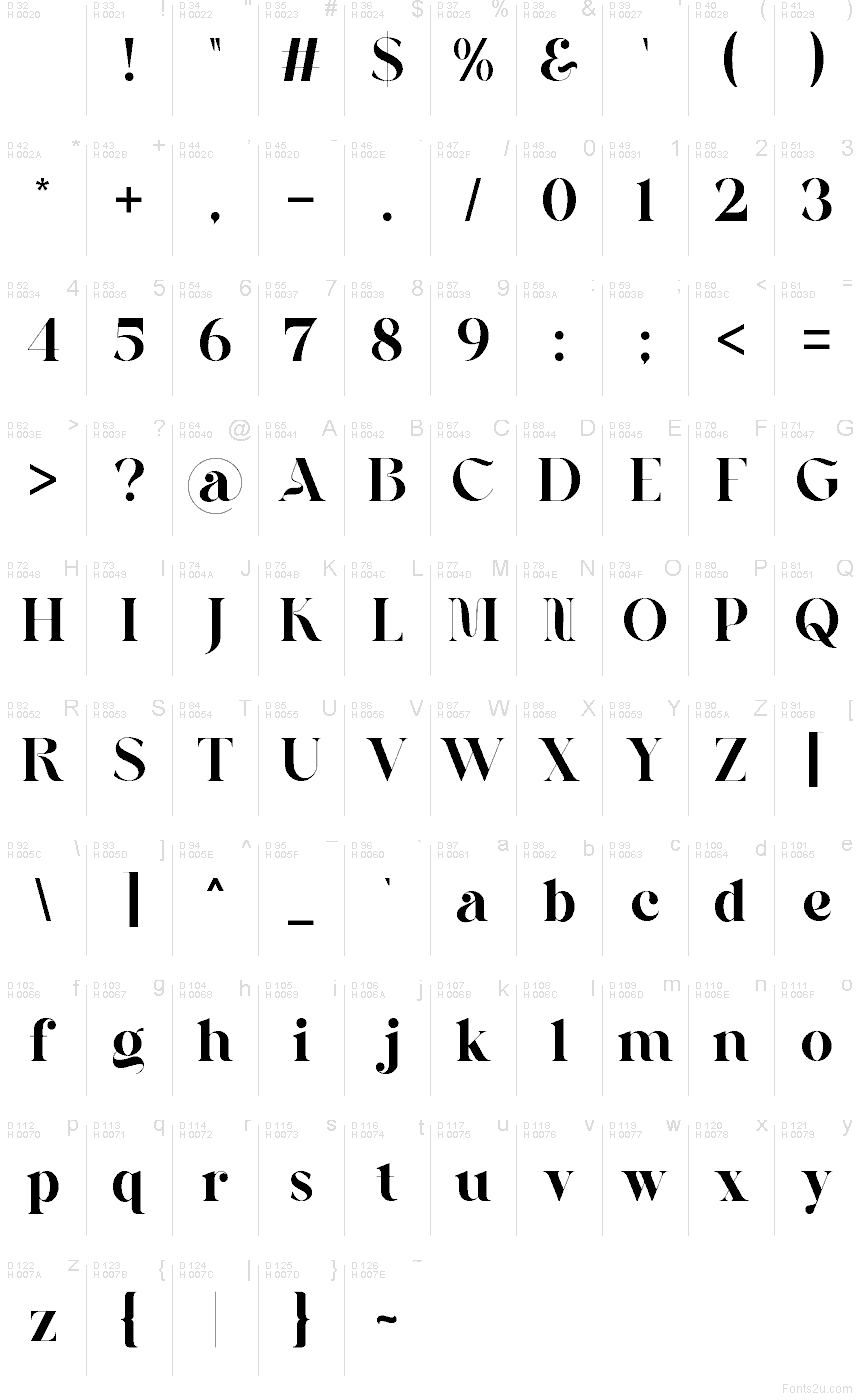
Rellika, da Ermedia Studio, é uma fonte com serifa gratuita que apresenta um contraste marcante entre traços grossos e finos e uma abordagem nitidamente ornamental nas curvas. Finas linhas capilares curvam-se em traços cheios e arredondados. Suas serifas afiadas e detalhes ondulados conferem às letras um visual mais refinado do que o de uma serifa editorial tradicional.
Editoriais de moda e embalagens de perfume aproveitam muito bem essa fusão de precisão e extravagância. Convites formais oferecem outro cenário propício para suas curvas amplas e junções delicadas. As proporções exageradas conferem a esses projetos uma elegância teatral enraizada no lettering de exibição tradicional.